싸인은 단순한 서명이 아니라 나를 표현하는 특별한 상징이 될 수 있어요. 내가 만든 싸인이 하나의 브랜드가 될 수도 있죠! 🎨
내가 생각했을 때, 멋진 싸인은 쉽고 개성 있는 스타일이 중요해요. 초보자라도 몇 가지 원칙만 알면 금방 나만의 멋진 싸인을 만들 수 있답니다! ✍
이제 초보자도 쉽게 따라 할 수 있는 특별한 싸인 만들기 방법을 알아볼까요? 🚀
나만의 싸인을 가지는 이유 ✨
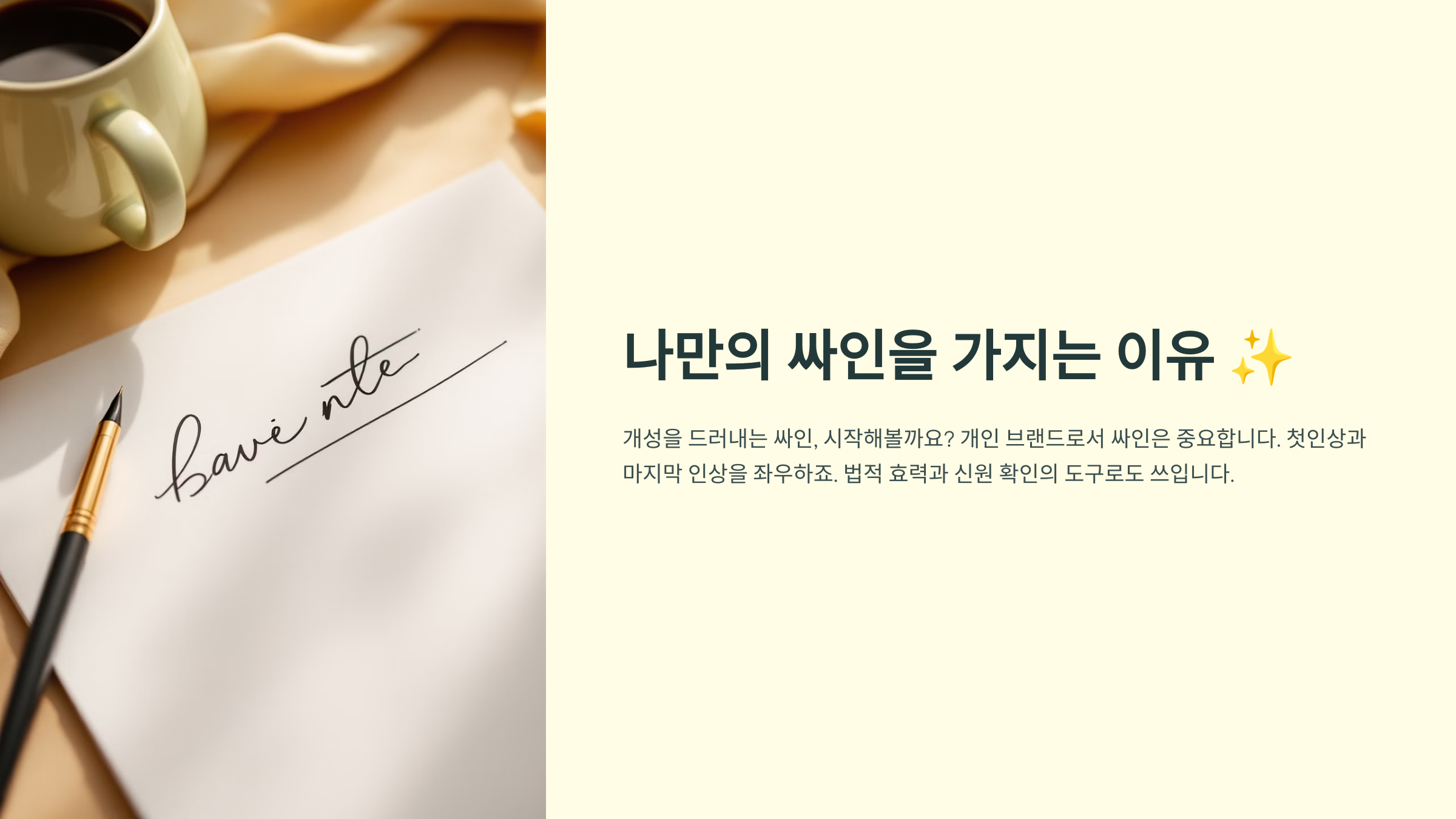
싸인은 단순한 서명이 아니라 자신을 표현하는 개성이 담긴 도구예요. 유명인들은 싸인 하나만으로도 자신을 상징하는 브랜드를 만들기도 하죠. 하지만 일반인들에게도 싸인은 매우 유용해요! 🖊
🔹 공식 문서에서 나를 대표하는 서명 계약서, 신분증, 은행 서류 등을 작성할 때 싸인을 사용해요. 단순한 이름 대신 개성 있는 싸인을 하면 신뢰감을 높일 수 있어요.
🔹 브랜딩 효과 나만의 싸인은 하나의 브랜드가 될 수 있어요. 예술가, 디자이너, 작가 등 개성을 드러내야 하는 직업군에서는 필수적이죠!
🔹 도장 대신 간편한 인증 도구 공식적인 자리에서도 싸인을 활용하면 손쉽게 신분을 증명할 수 있어요. 특히, 디지털 싸인이 활성화된 지금은 더욱 중요하답니다! 💻
🖋 싸인이 가지는 의미 정리 🔍
싸인의 용도 설명 신분 확인 계약서, 공문서 등에서 본인 인증 개성 표현 이름을 스타일링해 나만의 아이덴티티 확립 브랜딩 효과 유명인, 아티스트, 사업가 등 브랜드 이미지 구축 디지털 시대 필수 전자 문서, 이메일 서명 등에 활용 가능 싸인은 단순한 서명을 넘어 나를 대표하는 특별한 도구예요! 이제 초보자도 쉽게 따라 할 수 있는 기본 싸인 연습법을 배워볼까요? ✍
초보자를 위한 기본 싸인 연습법 🖊
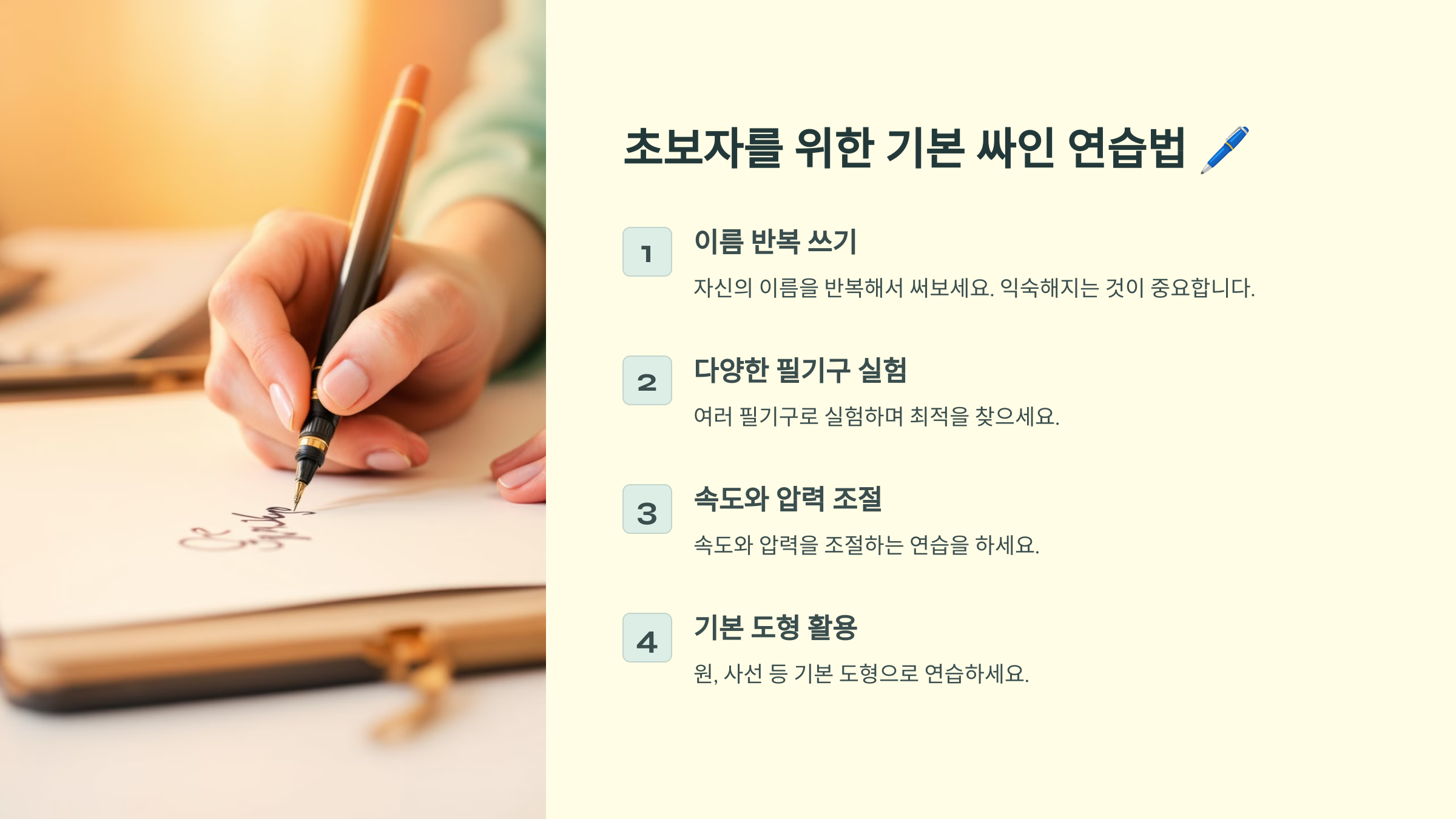
처음 싸인을 만들 때 너무 어렵게 생각할 필요 없어요! 기본적인 연습만 잘하면 누구나 멋지고 개성 있는 싸인을 만들 수 있어요. ✍
🔹 편한 필기체를 찾아라 자연스럽게 손이 가는 필기체가 있어요. 너무 억지로 꾸미려 하지 말고, 가장 편하게 쓸 수 있는 스타일을 찾는 게 중요해요!
🔹 이니셜을 활용하라 풀네임을 모두 쓰는 것도 좋지만, 이니셜을 강조하면 훨씬 간결하고 세련된 느낌을 줄 수 있어요. 예를 들어, ‘J.H.Kim’처럼 만들 수도 있죠!
🔹 속도를 조절하며 연습하기 빠르게 쓰면 날렵하고 강렬한 느낌이 들고, 천천히 쓰면 정돈된 인상을 줘요. 여러 속도로 써보면서 나에게 맞는 스타일을 찾아보세요. ⏳
📄 초보자를 위한 단계별 싸인 연습법 🖊
단계 연습 방법 1단계 이름을 다양한 필기체로 써보기 2단계 이니셜을 강조한 스타일 시도하기 3단계 선 굵기와 크기 조절하면서 테스트 4단계 속도를 조절하며 스타일 정하기 5단계 자연스럽게 싸인이 나올 때까지 반복 연습 이제 기본 연습법을 익혔으니, 본격적으로 이름을 활용한 싸인 스타일을 살펴볼까요? 🎨
이름을 활용한 싸인 스타일 3가지 🎨
싸인을 만들 때 이름을 어떻게 활용하느냐에 따라 느낌과 개성이 달라져요. 싸인 스타일을 선택할 때는 간결하면서도 기억에 남는 디자인을 고려해야 해요. ✍
🔹 이니셜형 싸인 이니셜만 활용한 싸인은 심플하면서도 강렬한 인상을 줄 수 있어요. 예를 들어, ‘J.H.Kim’처럼 점을 활용하거나, ‘JK’처럼 두 글자만 쓰는 방식도 좋아요.
🔹 필기체형 싸인 자연스럽게 흐르는 필기체를 활용하면 고급스럽고 부드러운 느낌을 줄 수 있어요. 특히, 서명이 필요한 공식 문서에서 활용하기 좋아요.
🔹 그래픽형 싸인 이름을 변형하거나 특별한 장식을 추가하면 개성이 강한 싸인이 돼요. 예를 들어, 이니셜에 별 ⭐, 하트 ❤, 번개 ⚡ 같은 기호를 추가하면 더욱 특별해 보이죠!
🖋 싸인 스타일별 비교 🔍
스타일 특징 추천 대상 이니셜형 간결하고 세련된 느낌 비즈니스 전문가, 공식 문서 서명 필기체형 부드럽고 우아한 분위기 예술가, 디자이너, 작가 그래픽형 개성 넘치는 창의적 스타일 연예인, 크리에이터, 인플루언서 이제 원하는 스타일을 선택해서 직접 연습해보면 좋아요! 😃 유명인들의 싸인을 참고하면 더욱 도움이 될 수도 있겠죠? 🌟
유명인의 싸인 스타일 참고하기 🌟
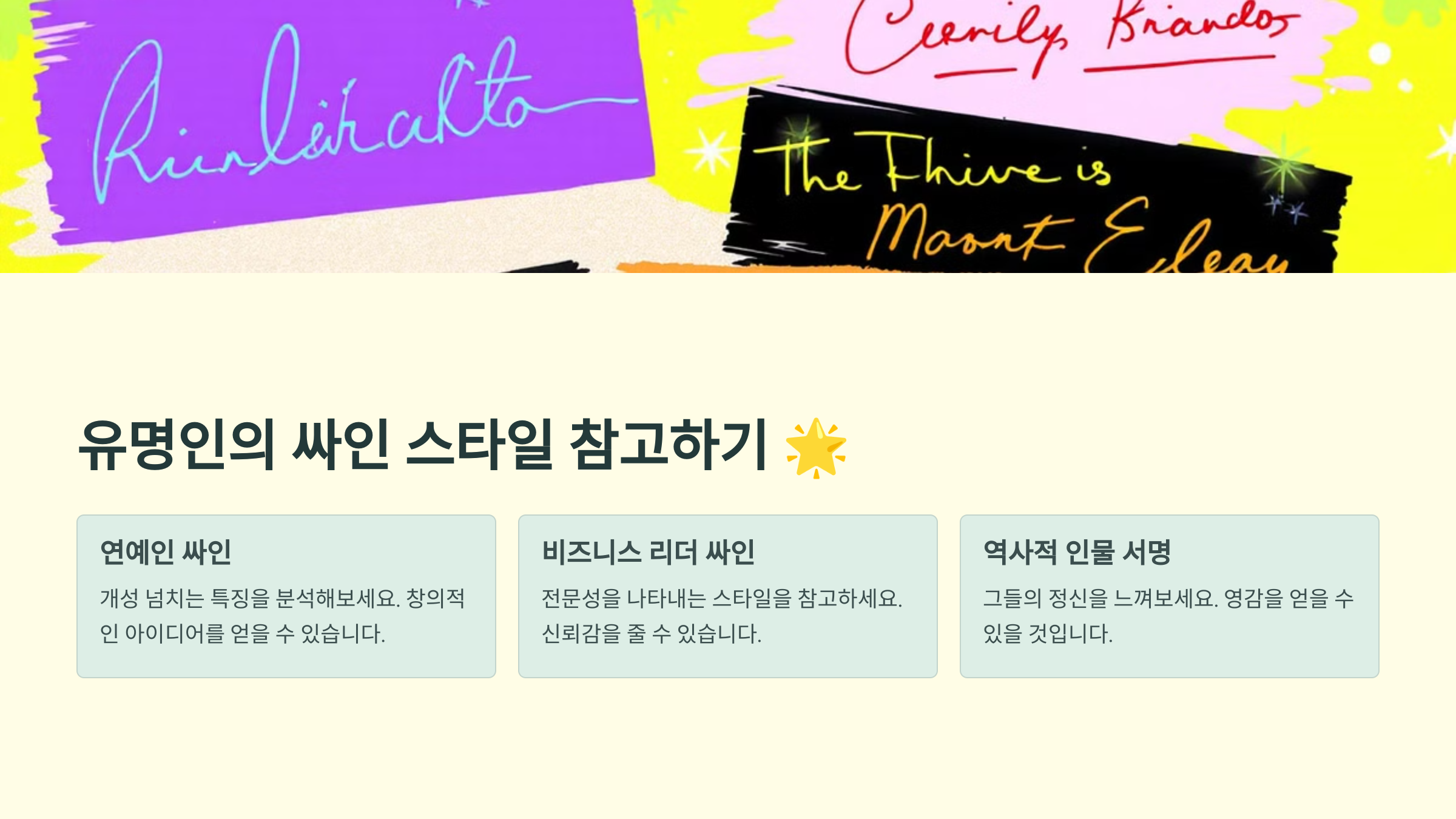
유명인들의 싸인은 단순하지만 강렬한 개성이 담겨 있어요. 어떤 싸인이든 한눈에 알아볼 수 있도록 디자인된 것이 특징이죠. 🖊
🔹 스티브 잡스 – 간결한 필기체 스타일 잡스의 싸인은 간결하면서도 세련된 필기체예요. 전체적인 흐름이 깔끔하고 현대적인 느낌을 주죠.
🔹 마이클 조던 – 강렬한 곡선과 속도감 조던의 싸인은 필기체이면서도 속도감이 강조된 스타일이에요. 스포츠 스타답게 역동적인 느낌이 살아 있어요. 🏀
🔹 테일러 스위프트 – 감각적인 필체와 장식 요소 스위프트는 부드러운 필체와 함께 별 ⭐ 같은 장식을 추가해 싸인을 더욱 특별하게 만들었어요.
📜 유명인의 싸인 스타일 분석 🔍
유명인 싸인의 특징 느낌 스티브 잡스 깔끔한 필기체, 미니멀한 디자인 혁신적이고 세련된 느낌 마이클 조던 역동적인 곡선과 속도감 스포츠 스타다운 강렬함 테일러 스위프트 부드러운 필기체 + 아이콘 장식 우아하고 감각적인 분위기 BTS 각 멤버마다 독특한 개성 반영 트렌디하고 유니크한 스타일 이처럼 싸인은 단순하지만 인상적인 것이 중요해요! 이제 꾸준한 연습을 통해 나만의 싸인을 완성하는 방법을 알아볼까요? 🖊
멋진 싸인을 위한 꾸준한 연습법 📄
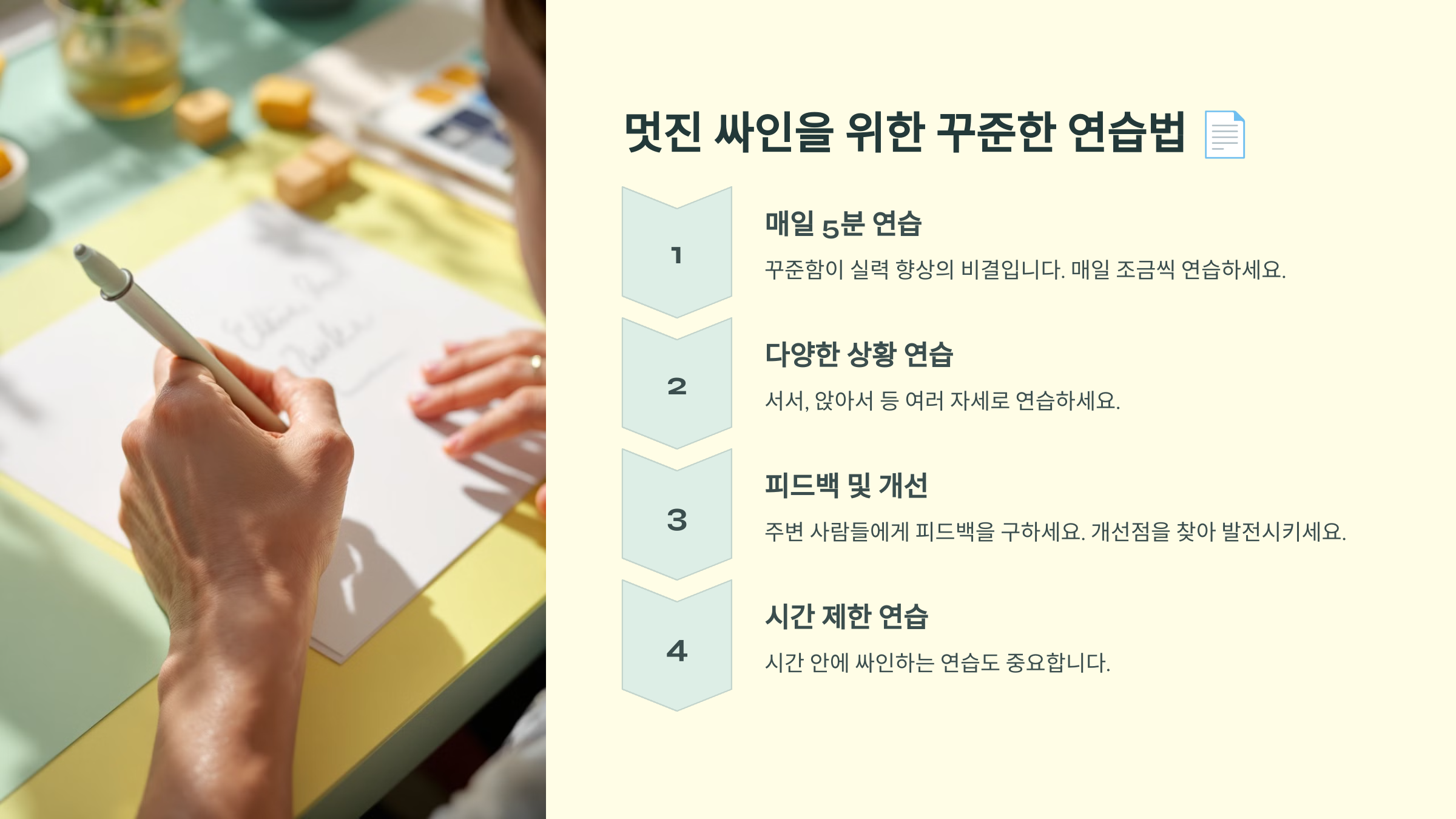
멋진 싸인을 만들기 위해서는 단순히 한 번 그려보는 것보다 꾸준한 연습이 중요해요. 손에 익을 때까지 반복하면 자연스럽고 멋진 싸인이 완성되죠. ✍
🔹 여러 가지 스타일을 시도해보기 이니셜형, 필기체형, 그래픽형 등 다양한 스타일을 시도해 보면서 나에게 맞는 싸인을 찾아보세요.
🔹 사인의 크기 조절하기 너무 작거나 크면 활용하기 어려울 수 있어요. A4 용지와 카드 크기에서 모두 잘 보이는 크기로 연습하세요.
🔹 빠르게 써보면서 손에 익히기 처음엔 천천히 연습하되, 나중에는 실전처럼 빠르게 싸인을 해보는 것이 좋아요. ✨
📌 단계별 싸인 연습법 🖊
단계 연습 방법 1단계 이름을 다양한 스타일로 써보기 2단계 이니셜이나 기호를 추가해보기 3단계 속도를 조절하면서 싸인 연습 4단계 다양한 크기로 싸인 연습 5단계 실전처럼 자연스럽게 싸인하기 이제 손에 익도록 꾸준히 연습하면서 나만의 싸인을 완성해보세요! 😃 디지털 시대에는 전자 싸인도 필수인데요, 이제 전자 싸인에 대해 알아볼까요? 💻
디지털 싸인도 중요한 시대! 💻
디지털 시대가 되면서 전자 싸인(디지털 서명)의 활용도가 높아졌어요. 이제 계약서, 문서, 이메일 등 다양한 곳에서 전자
싸인이 필수 요소가 되고 있어요. ✍
🔹 전자 싸인이란? 전자 서명 또는 디지털 싸인은 온라인 문서에 서명하는 방법이에요. PDF, 워드 파일, 이메일 등에 싸인을 삽입할 수 있어요.
🔹 어디에서 사용할까? 계약서, 금융 거래, 공문서 등 법적 효력이 필요한 문서에 활용돼요. 비즈니스 환경에서도 빠르고 편리하게 싸인을 주고받을 수 있어요.
🔹 전자 싸인 만드는 방법 스마트폰, 태블릿, 스타일러스 펜 등을 이용해서 싸인을 만들고, PNG 파일로 저장하면 쉽게 활용할 수 있어요. ✅
📌 인기 있는 전자 싸인 도구 💾
도구 특징 DocuSign 계약서, 법적 문서에 활용 가능 Adobe Sign PDF 문서에 직접 서명 가능 HelloSign Google Drive와 연동 가능 SignEasy 모바일에서 간편한 전자 서명 이제는 디지털 싸인도 필수인 시대예요! 종이에만 싸인을 하던 시대는 끝났어요. 자주 묻는 질문(FAQ)도 확인해볼까요? ❓
FAQ ❓
Q1. 초보자도 쉽게 멋진 싸인을 만들 수 있나요?
A1. 네! 기본적인 연습을 통해 누구나 멋진 싸인을 만들 수 있어요. 이니셜을 활용하거나, 필기체를 변형하는 방법부터 시작해 보세요. ✍
Q2. 싸인 스타일을 어떻게 정해야 하나요?
A2. 싸인 스타일은 본인의 개성과 활용 목적에 따라 다를 수 있어요. 비즈니스용이라면 간결한 이니셜형, 예술적이라면 필기체형, 독창성을 원한다면 그래픽형이 좋아요. 🎨
Q3. 한글 싸인과 영어 싸인 중 어떤 것이 더 좋을까요?
A3. 한글 싸인은 부드럽고 독창적인 느낌을 주고, 영어 싸인은 간결하고 국제적인 이미지를 줄 수 있어요. 본인의 용도에 맞게 선택하는 것이 중요해요! 🖊
Q4. 싸인을 연습할 때 가장 중요한 점은 무엇인가요?
A4. 일관된 스타일을 유지하는 것이 가장 중요해요. 또한, 싸인의 크기와 속도를 조절하며 연습하는 것도 도움이 돼요. 🏆
Q5. 전자 싸인은 어떻게 만들 수 있나요?
A5. 태블릿이나 스마트폰을 이용해 스타일러스 펜으로 싸인을 작성한 후 PNG 파일로 저장하면 전자 싸인을 쉽게 만들 수 있어요. ✅
Q6. 싸인을 만들 때 피해야 할 실수는?
A6. 너무 복잡하게 만들면 싸인을 빠르게 하기 어렵고, 일관성이 떨어질 수 있어요. 또한, 너무 단순하면 개성이 부족할 수도 있어요. 🔄
Q7. 유명인의 싸인을 따라 해도 괜찮을까요?
A7. 참고는 좋지만, 그대로 따라 하는 것은 추천하지 않아요. 유명인의 스타일을 참고하면서 나만의 개성을 추가하는 것이 더 좋아요. 🌟
Q8. 싸인을 바꾸면 운도 바뀐다는 말이 사실인가요?
A8. 과학적인 근거는 없지만, 자신감이 생기고 이미지가 달라질 수 있는 것은 사실이에요. 성공한 사람들의 싸인을 보면 강렬한 개성이 담겨 있답니다! 🚀
지금까지 초보자도 쉽게 따라 할 수 있는 싸인 만드는 법을 알아봤어요! 이제 직접 연습하면서 나만의 멋진 싸인을 완성해보세요. ✨